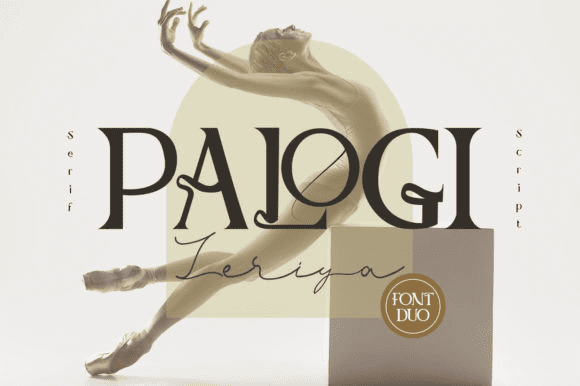
Название: Palogi Font
Палоги - это невероятно элегантный и четкий дуэтный шрифт (засечка и шрифт).
Этот универсальный скриптовый шрифт имеет широкий спектр применения, начиная от поздравительных открыток и заканчивая заголовками, и гарантированно добавит романтической атмосферы вашему следующему проекту.